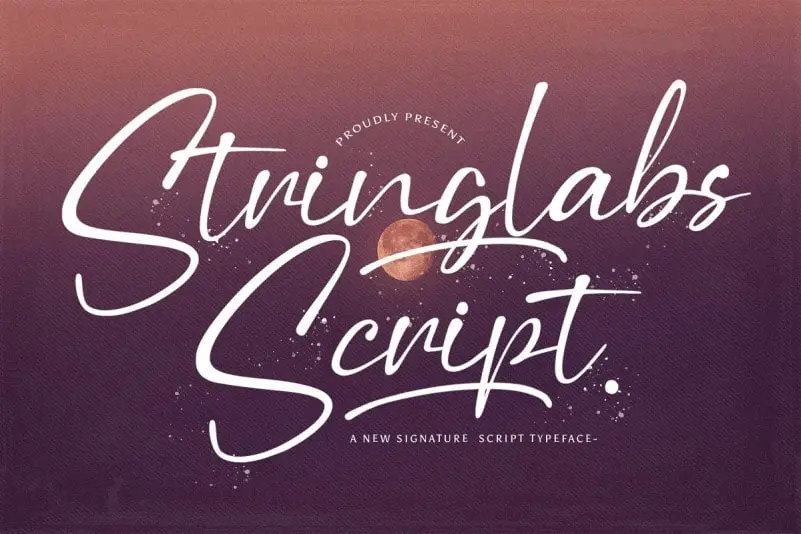
Stringlabs Script Font – Download Grátis
A Stringlabs Script Font é uma fonte elegante inspirada nos traços únicos do gosto pessoal que faz escrever único e divertido. Este tipo de escrita inovadora, moderna e cuidadosamente escrita oferece caracteres belos e equilibrados, tornando-a perfeita para um amplo leque de projetos. Adicione-a aos seus ideais mais criativos e observe como ela os anima. Seja você o próximo a experimentar essa fonte única e emocionante na sua próxima proposta gráfica ou projeto de identidade visual.